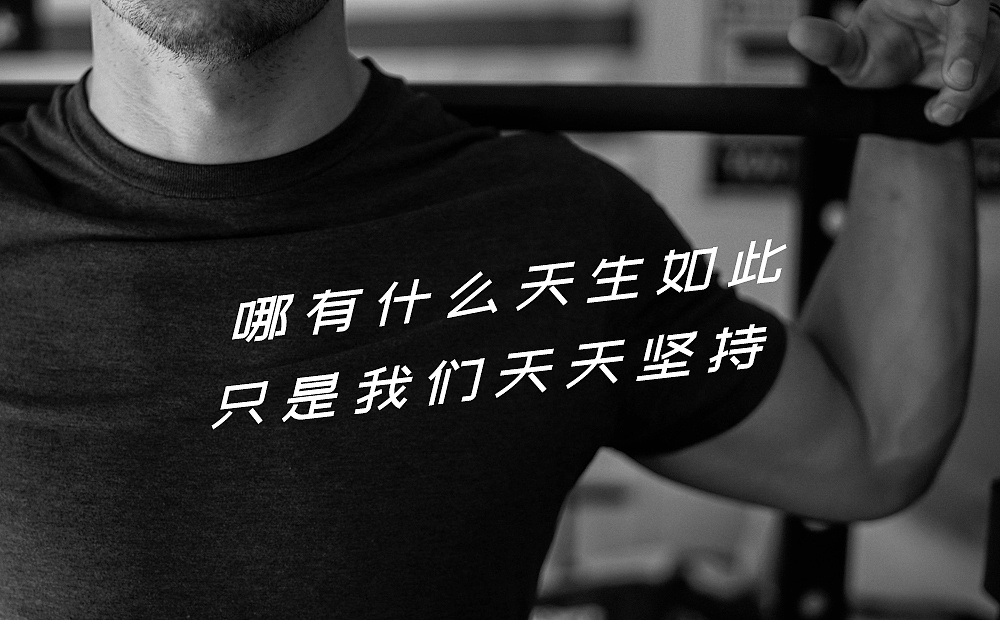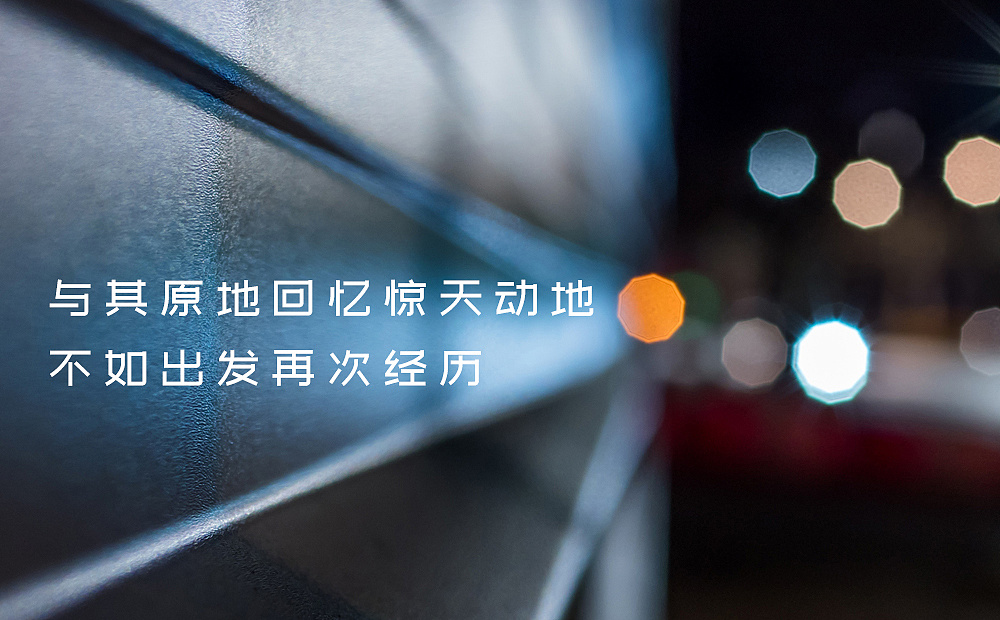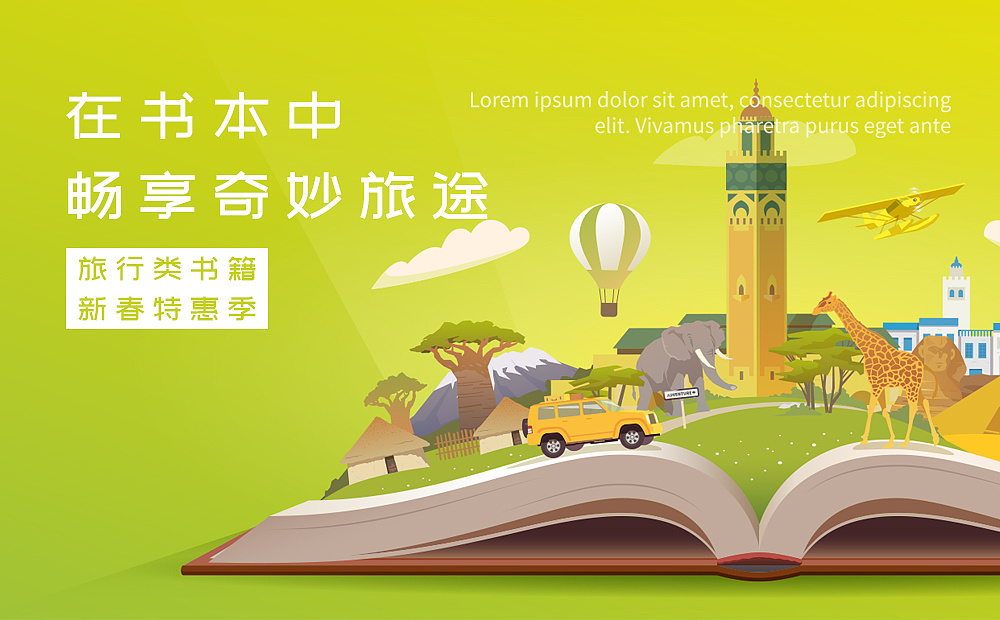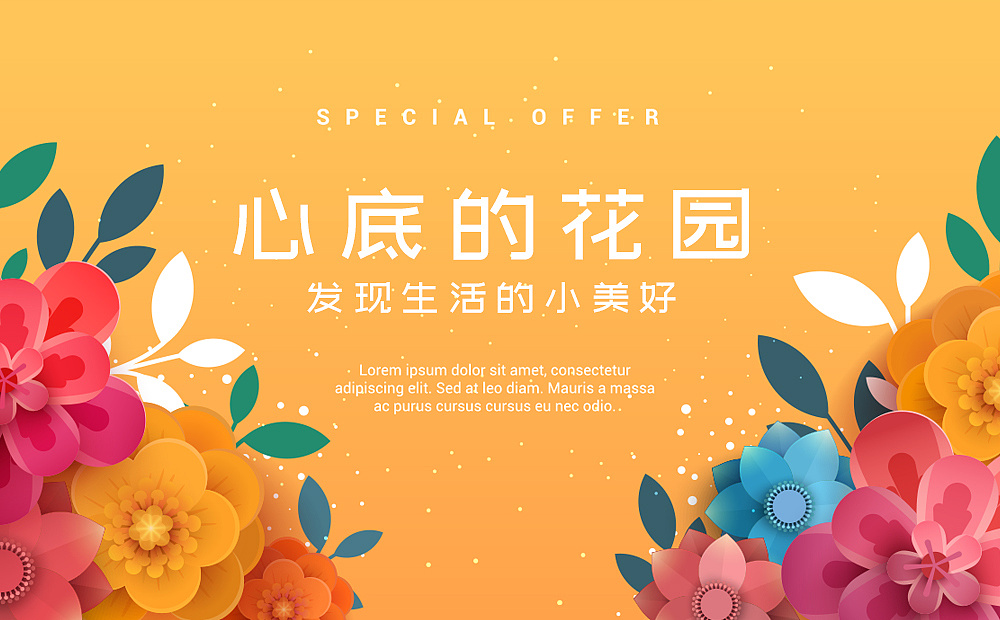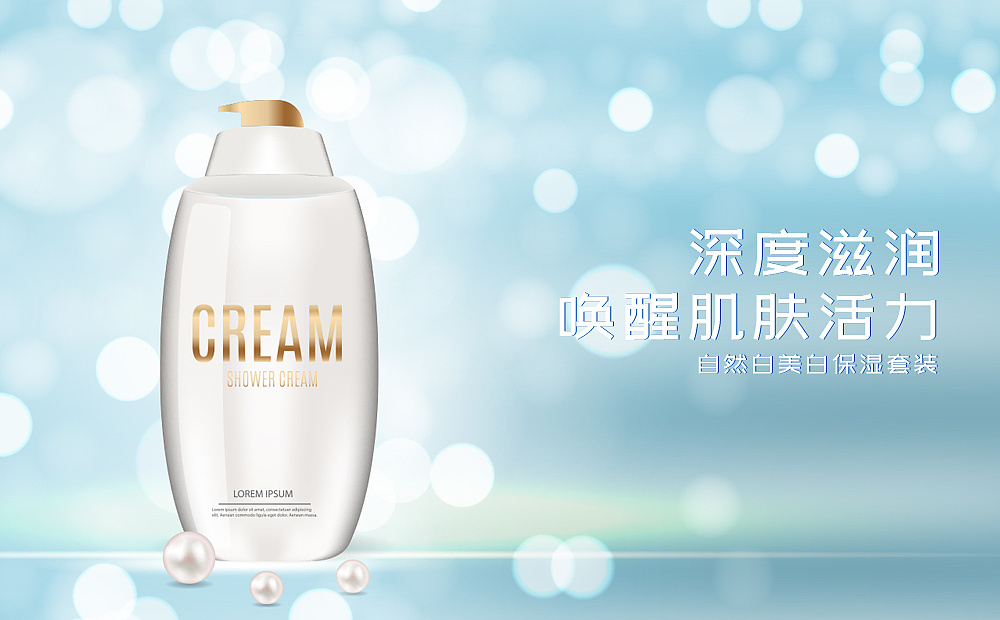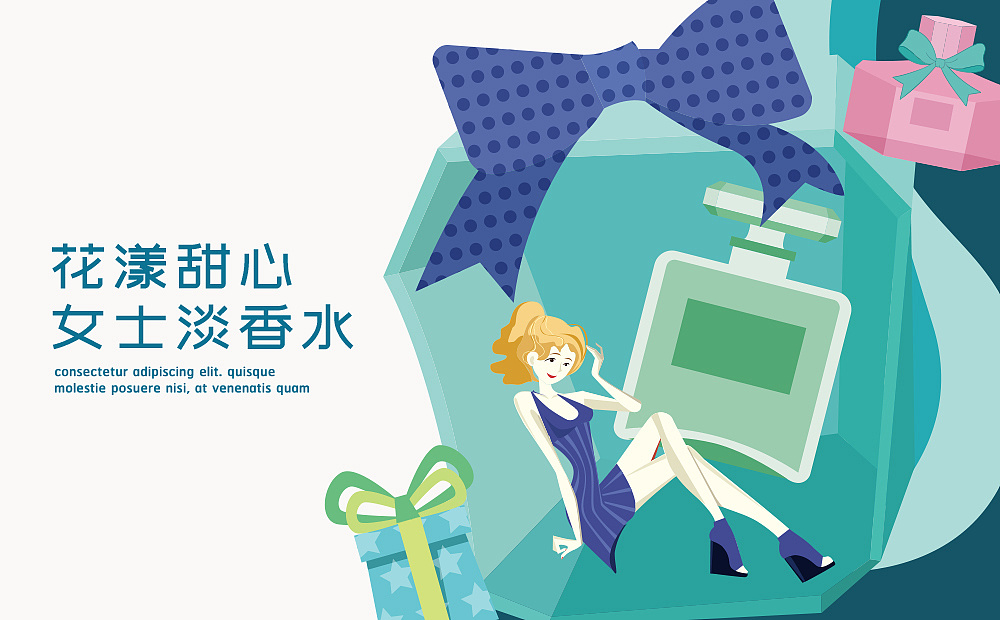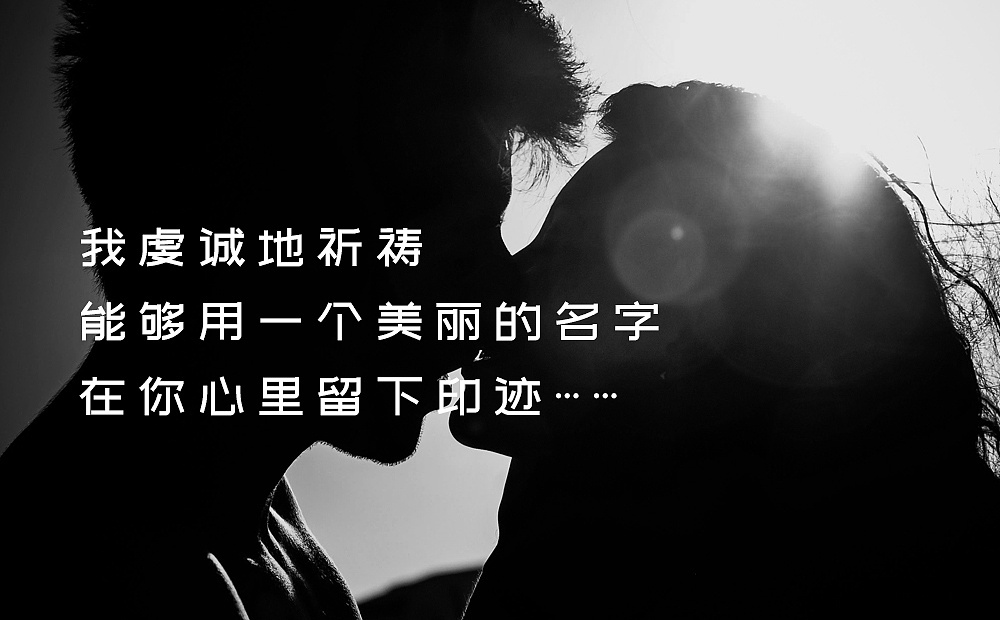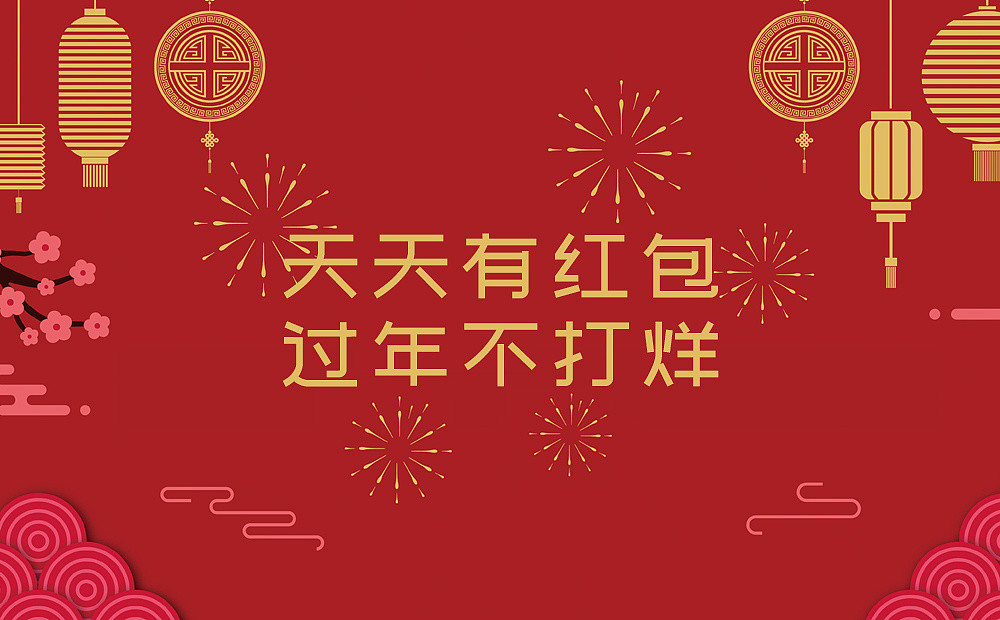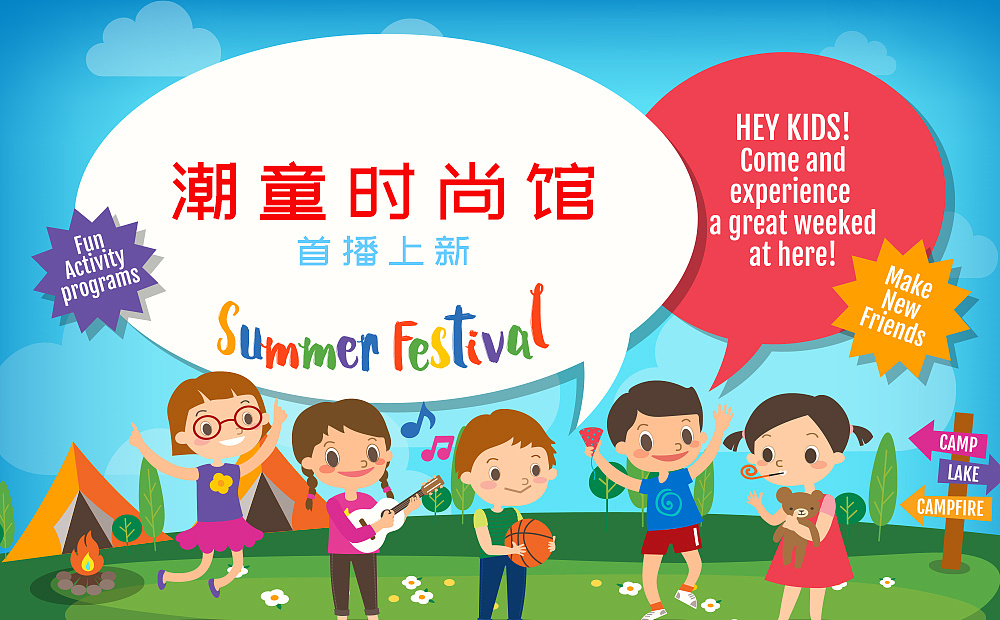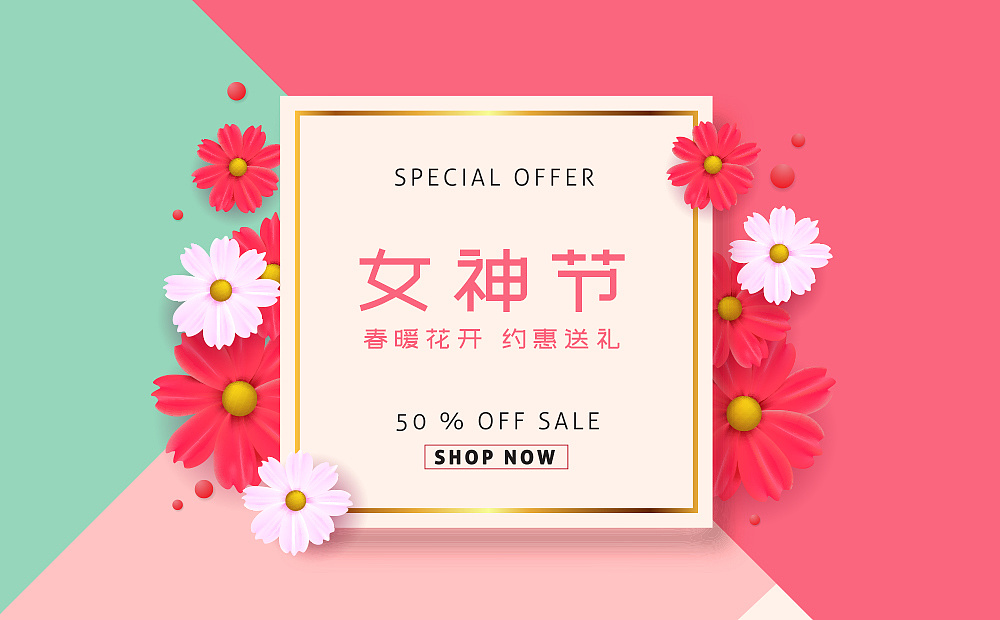
站酷文艺体:简洁有力清新淡雅的公益字体
站酷文艺体,由刘兵克工作室团队、以及刘兵克字体设计直播课的近50位学员共同创作完成,经历多个步骤,历时超过半年时间,字体完成后,由设计师郑庆科完成了最终的字库生成工作。
站酷文艺体,由字体设计师刘兵克确定字形和规范,结构上选用了略扁的形态,其笔画粗细基本保持一致,字形新颖独特,简洁有力,清新淡雅,文艺范十足。在字形细节里,适当的圆角设计,“口”字形部件右上角的竖线设计,以及撇捺笔画的曲直对比设计,这些崭新的形态以及组合,都让这款字体具备了更多的独创性,当然,在创新和“脱俗”的同时,站酷文艺体也保持了上佳的可读性和流畅度,所以,这款字体,在应用环境也较为广泛,无论是标题字,还是正文字,都会呈现出良好、舒适的视觉感受。
西文丑的一批
逗号离前面的字太远了
比较适合稳重,淡雅的风格